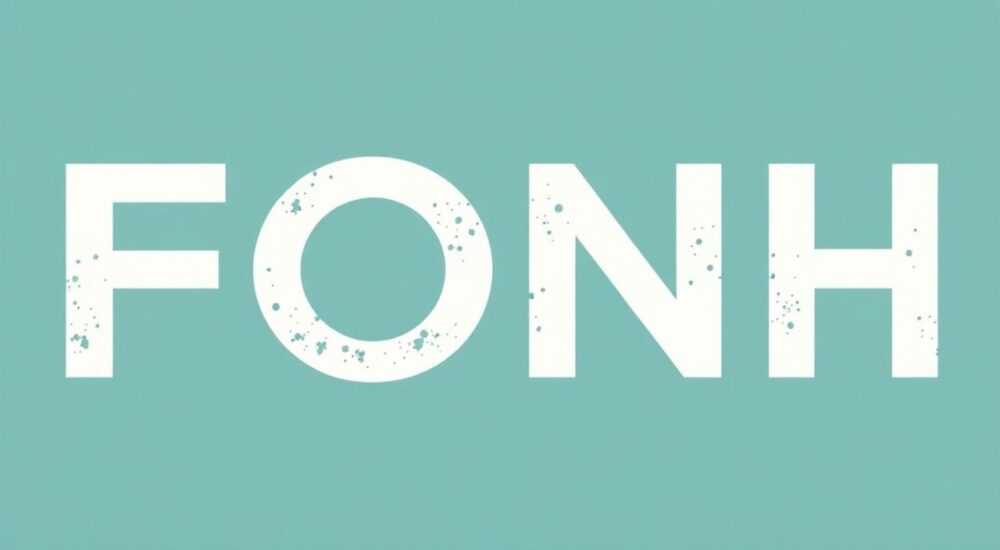
Как определить шрифт по картинке в фотошопе
Определение шрифта по изображению — задача, с которой регулярно сталкиваются дизайнеры, верстальщики и маркетологи. Когда перед вами находится логотип, обложка или скриншот с неизвестным типографским решением, важно быстро и точно установить его название, чтобы сохранить стиль, воссоздать макет или проверить лицензионные ограничения. Фотошоп, будучи мощным инструментом графического редактирования, предлагает как встроенные, так и сторонние возможности для идентификации шрифтов.
Чтобы определить шрифт по картинке в Photoshop, используйте функцию «Поиск шрифтов» (на основе Adobe Fonts) или выделите текстовый слой с помощью инструмента «Текст» — если он доступен. Для изображений с растровым текстом применяйте онлайн-сервисы вроде WhatTheFont или Font Squirrel Matcherator, загружая фрагмент из фотошопа.
Как работает идентификация шрифтов: основы и принципы
Перед тем как переходить к практическим шагам, важно понять, что такое шрифт и как его можно распознать. Шрифт — это набор графических символов (букв, цифр, знаков), объединённых единым стилем. Каждый шрифт имеет уникальные характеристики: форму засечек, пропорции символов, высоту x-height, угол наклона, толщину штрихов и другие детали.
Идентификация шрифта по изображению возможна двумя путями: через анализ векторного/текстового слоя или через распознавание растрового текста. В первом случае, если текст в PSD-файле остался в виде редактируемого слоя, достаточно выбрать его инструментом «Текст» и посмотреть параметры в панели свойств. Во втором — когда текст «запечён» в пиксели, требуется внешний анализ.
Фотошоп сам по себе не является специализированным инструментом для OCR (оптического распознавания символов) шрифтов, но интеграция с облачными сервисами Adobe позволяет частично решить эту задачу. Однако точность зависит от качества изображения, контрастности, размера текста и наличия искажений.
Представьте: вы получили макет от клиента в формате JPG. Текст на изображении читаем, но редактировать его нельзя. Ваша задача — подобрать тот же шрифт для нового баннера. От того, насколько точно вы его определите, зависит визуальная целостность проекта.
Полезно знать: Чем выше разрешение исходного изображения и чётче границы символов, тем выше вероятность корректного распознавания шрифта.
Встроенные инструменты Photoshop для определения шрифтов
Adobe продолжает развивать экосистему Creative Cloud, и одна из её полезных функций — поиск шрифтов по образцу. Начиная с версии Photoshop 2020, в программу добавлена интеграция с Adobe Fonts (ранее Typekit). Это позволяет не только использовать тысячи лицензионных шрифтов, но и искать похожие по внешнему виду.
Для начала убедитесь, что вы авторизованы в своей учётной записи Adobe. Без этого доступ к облачным функциям будет ограничен. Затем откройте изображение и выделите участок с текстом с помощью инструмента «Прямоугольная область» (M).
Нажмите правой кнопкой мыши по выделению и выберите пункт «Поиск шрифтов» (Search for Fonts). Если этот пункт неактивен, значит, текст слишком мал, размыт или система не распознала его как символы. Также важно, чтобы в настройках было включено соединение с интернетом.
Если всё сделано правильно, Photoshop отправит фрагмент в облако Adobe, где с помощью ИИ сравнят его с базой данных шрифтов. Через несколько секунд вы получите список наиболее похожих вариантов, с указанием названия, производителя и примера начертания.
Условия успешного поиска
• Текст должен быть горизонтальным, без поворота и искажений.
• Минимальный размер символов — 12 пикселей в высоту.
• Высокий контраст между текстом и фоном (например, чёрный по белому).
• Отсутствие эффектов вроде свечения, размытия или текстур.
«Функция “Поиск шрифтов” работает лучше всего с чистыми, простыми шрифтами без декоративных элементов. Сложные рукописные или кастомные шрифты она часто не распознаёт.» — Алексей Миронов, арт-директор дизайн-студии TypoLab
Использование онлайн-сервисов совместно с Photoshop
Когда встроенные средства Photoshop не справляются, на помощь приходят специализированные онлайн-сервисы. Они используют более продвинутые алгоритмы машинного обучения и крупные базы данных. Работают они по одному принципу: вы загружаете изображение, сервис анализирует текст и предлагает варианты.
Photoshop здесь играет роль подготовительного инструмента. Вы вырезаете нужный фрагмент, улучшаете контрастность, удаляете фон и экспортируете в PNG или JPG. После этого результат отправляется на сайт.
Наиболее популярные платформы:
Сервис
База шрифтов
Точность
Особенности
WhatTheFont (MyFonts)
Более 130 000
Высокая
Автоматическое определение символов, предпросмотр в реальном времени
Font Squirrel Matcherator
Около 65 000
Средняя
Только бесплатные шрифты, хорошая работа с печатными стилями
Adobe Fonts Search
Более 20 000